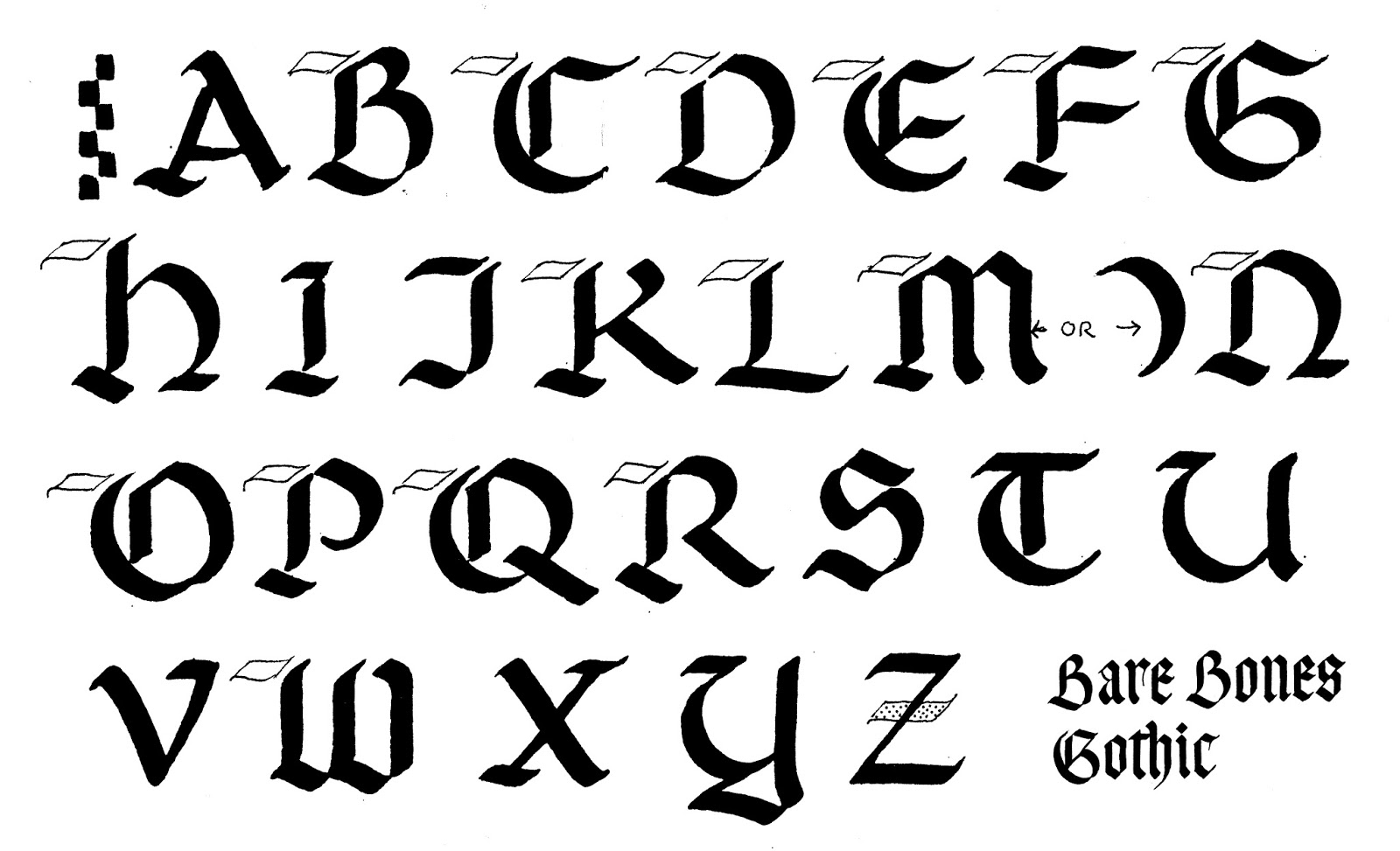
- У этого термина существуют и другие значения, см. Текстура. Шрифт Textura Quadrata
Тексту́ра (от лат. textura — ткань) — первая и основная разновидность готического письма. Своё название текстура получила за то, что покрывала страницу равномерно. Характерное отличие шрифтов данного типа — вытянутость букв.
Готический шрифт | Дизайн
Термин «Готический» обозначает семейство шрифтов, которыми писали в средневековой Европе задолго до возникновения полиграфической промышленности. Само название было придумано в 15 веке гуманистами итальянского возрождения, считавшими подобные шрифты «варварскими» («готы» — название древних германских племен, не имевших, однако, к данному способу начертания букв никакого отношения).
«Варварским», готическим шрифтам противопоставлялись антиквенные шрифты, созданные на основе римского монументального письма (см. главу Антиква).
Современные наборные гарнитуры, которые используются в полиграфии, представляют поздние формы готического шрифта, сложившиеся в Европе к концу 16-17 веков. Примером такого шрифта может служить гарнитура Fraktura (http://www.paratype.ru/help/term/terms.asp?code=146)
За свою пятивековую историю готический шрифт претерпел многочисленные преобразования. Его рукописные формы имеют огромное количество «почерков» различающихся по графике знаков. Печатный готический шрифт развивался и изменялся вместе с полиграфией, подчиняясь требованиям и ограничениям технологий печати, печатных форм и материалов. В результате, его ранние и поздние образцы стали существенно отличаться друг от друга.
В данном материале мы расскажем только про основные формы готического шрифта.
Текстура
В переводе с немецкого Textur означает ткань.
В Германии этот вид шрифта назывался Missal Schrift (литургический шрифт), или Gitter Schrift (Gitter – решетка). Эти названия прекрасно характеризуют и его форму, и назначение. В полиграфии, набор текстурой похож на плотный тканый узор (или узор тяжелой кованой решетки), сплошь покрывающий страницу. Знаки узкие, в конструкции букв преобладают жирные вертикальные штрихи.
Характерной особенностью готических текстов является отсутствие прописных букв (заглавные буквы, ИНИЦИАЛЫ, рисовались отдельно и по форме могли сильно отличаться от текстового шрифта). Слова не разделяли пробелом, их отделяли стоящей по центру строки жирной точкой. Строки выравнивали как по левому, так и по правому краю.
Для «красоты» написания в некоторых словах пропускали гласные буквы, а иногда целые слоги (пропущенные буквы обозначали сверху тонкой чертой – титлом). Такое написание не противоречило задачам книг того времени, так как текстурой писали канонические тексты. Читающий знал текст наизусть, написанное было всего лишь подсказкой, а книга, скорее, предметом культа, нежели источником информации.
Вопрос удобочитаемости, в современном его понимании, перед средневековыми писцами не стоял. Зато эстетические взгляды средневековья полностью отразились в характере шрифта. Трудно представить себе иное написание букв под стрельчатыми арками средневекового собора богато украшенного каменной резьбой. Стилистика оформления шрифта повторяет архитектурный стиль эпохи.